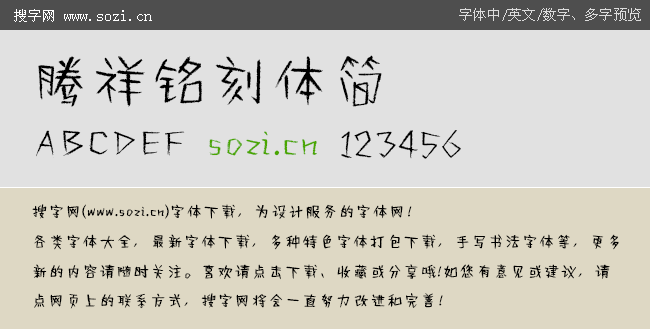
騰祥銘刻體簡(jiǎn)
搜字網(wǎng)提供一款騰祥銘刻體簡(jiǎn)中文藝術(shù)字體下載,該字體風(fēng)格鮮明、特點(diǎn)突出,筆畫(huà)古樸雅拙、精雕細(xì)刻,筆畫(huà)猶如用刀在石壁上一筆筆刻畫(huà)出的圖案。筆筆勁力、力透紙背、飛白顯露,彰顯刀刻之功?捎糜谟∷⒊霭、包裝設(shè)計(jì)、廣告設(shè)計(jì)、網(wǎng)頁(yè)設(shè)計(jì)等。